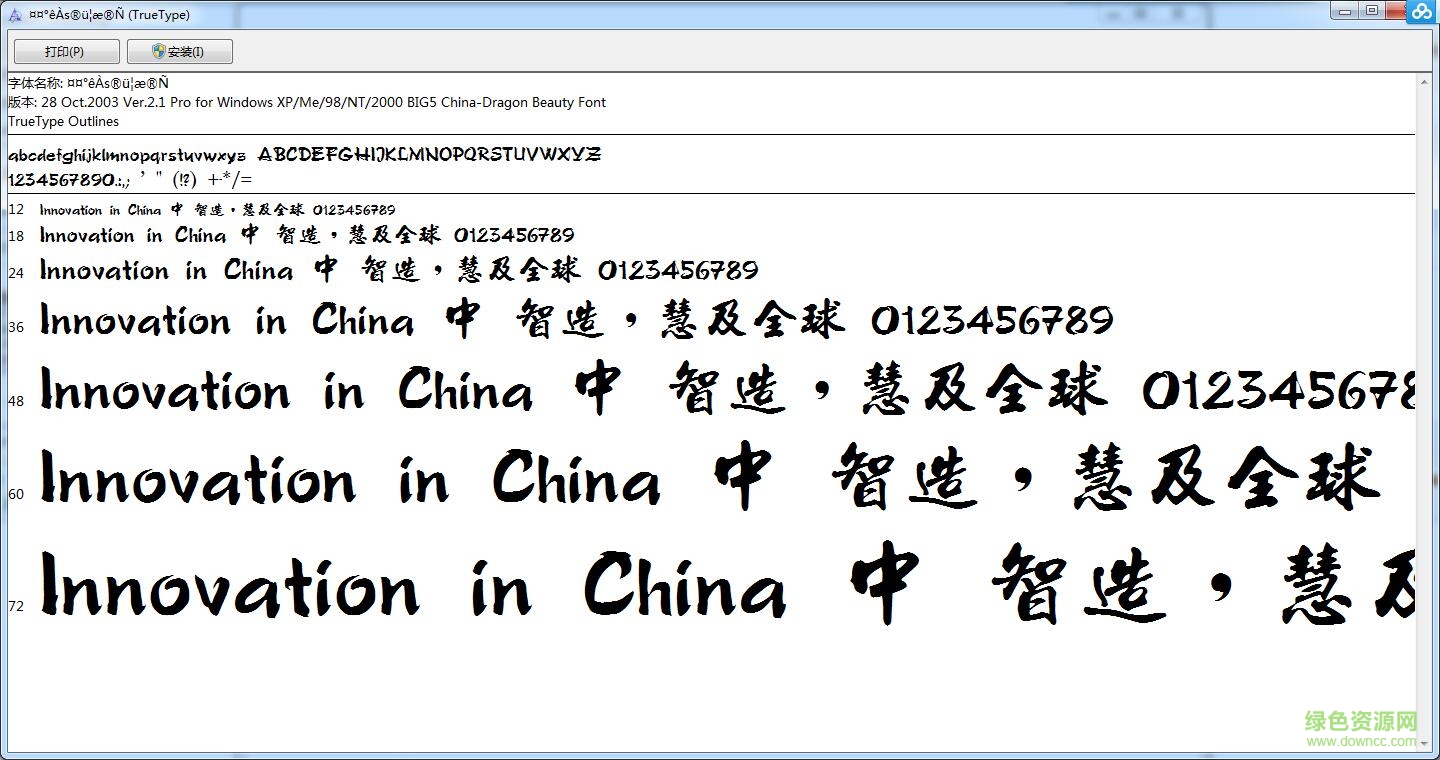
iddragonxing字體又叫中國龍海行書字體,該字體將飄逸的筆法和厚重的筆畫完美融合在一起,線條遒勁,寬博大氣,絕對(duì)讓人賞心悅目,神采奕奕有需要者歡迎免費(fèi)下載!
【調(diào)整輕重】
“險(xiǎn)中求平”是造型藝術(shù)美的一個(gè)重要因素,而要取得平衡,必須學(xué)會(huì)調(diào)整輕重。
【左右揮灑】
漢字有伸向左右的撇捺,他們向左右揮灑,不僅使字的神采得以展現(xiàn),而且可以方便地進(jìn)行行間的錯(cuò)落穿插,還能有效的調(diào)整輕重。因而“左右揮灑”成為行書布局的常用方式。
【上下貫穿】
貫穿行氣是行書布局謀篇的最重要的技巧
【錯(cuò)落大小】
由于“放縱體勢(shì)”,行書單字的高矮、寬窄、面積不盡相同,甚至懸殊很大。因此行書采用“縱有行,橫無列”的章法。由于一行字的字?jǐn)?shù)不固定,便容許寫得很長;由于橫向有一定的伸展余地,便容許寫得很寬。